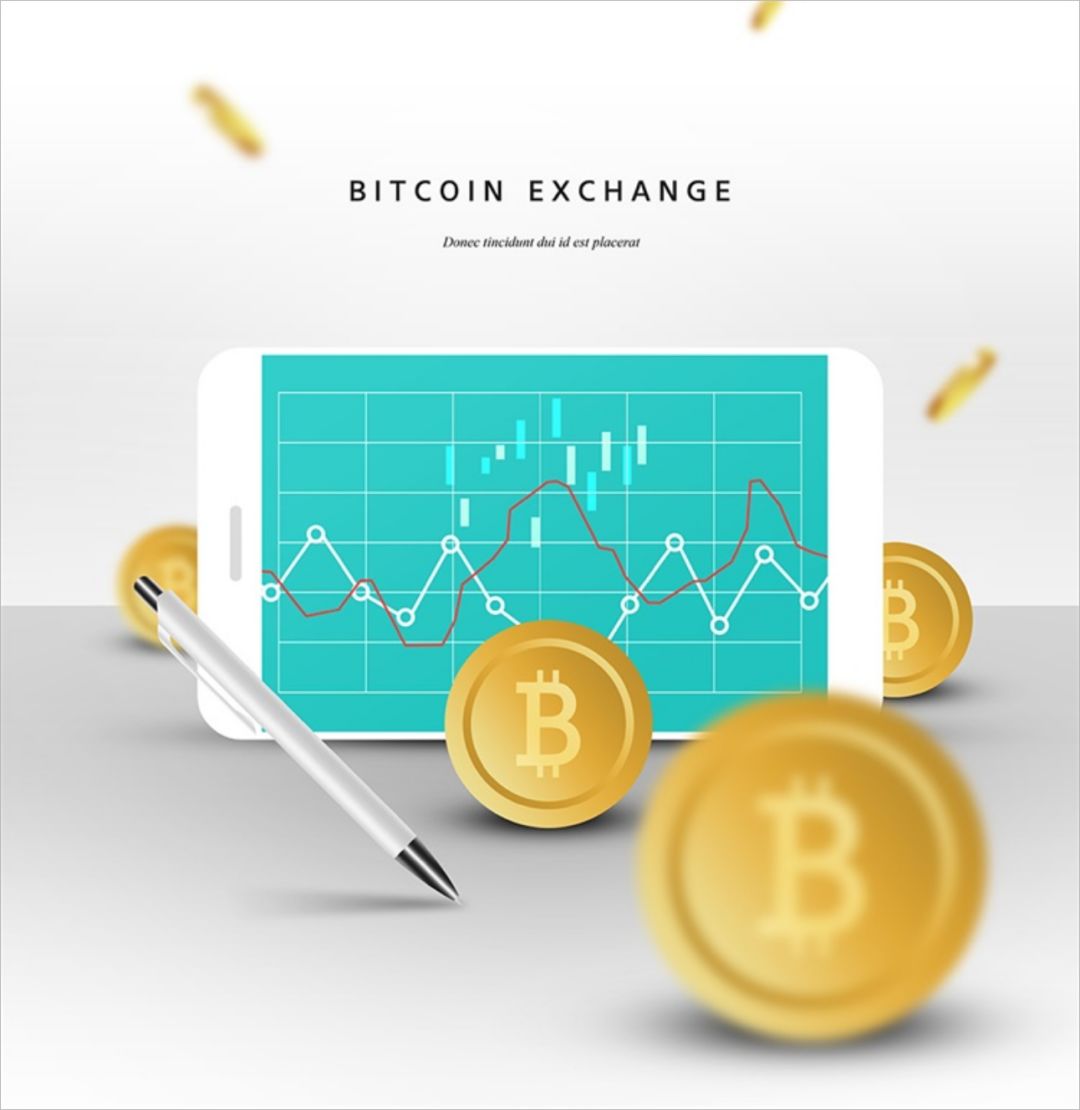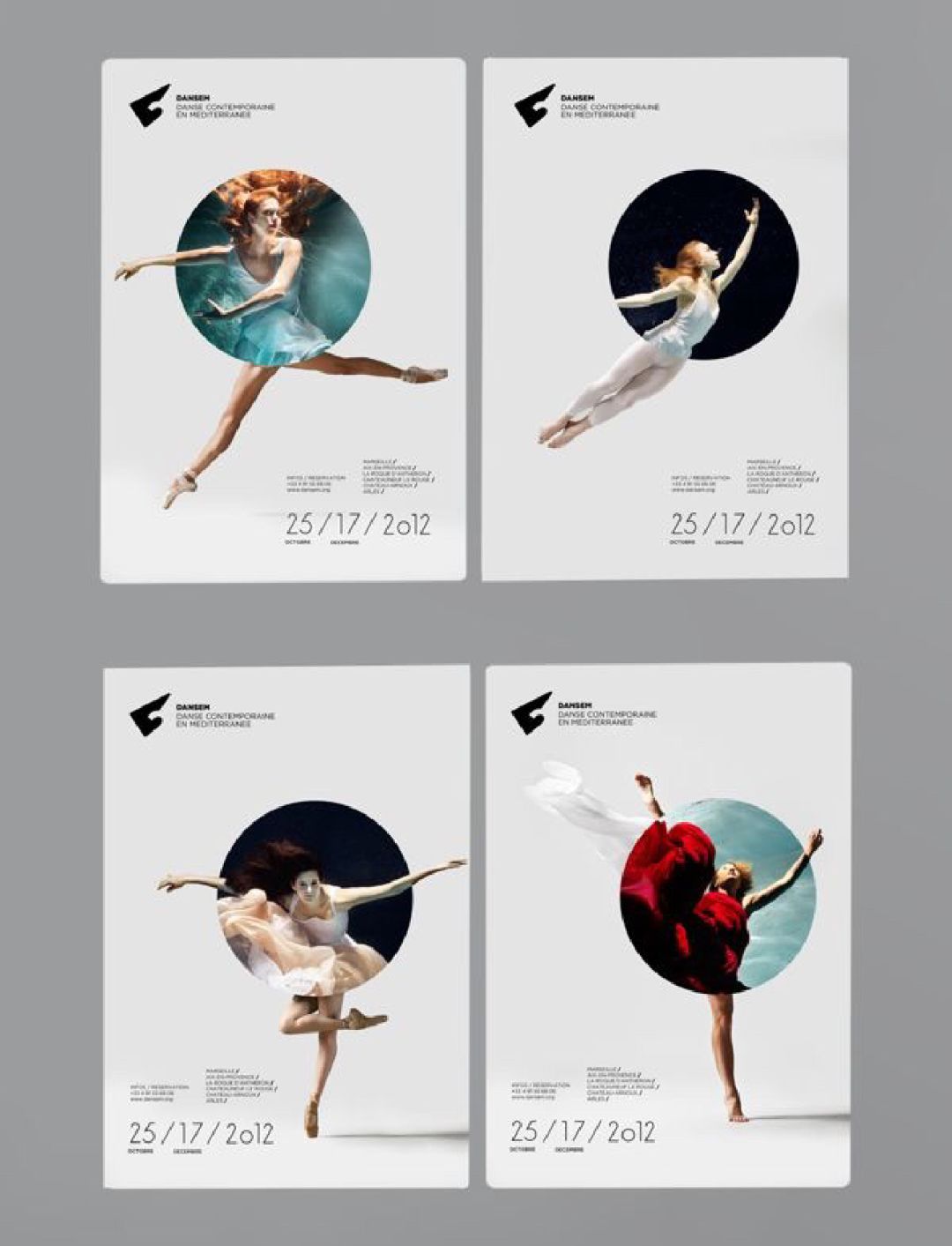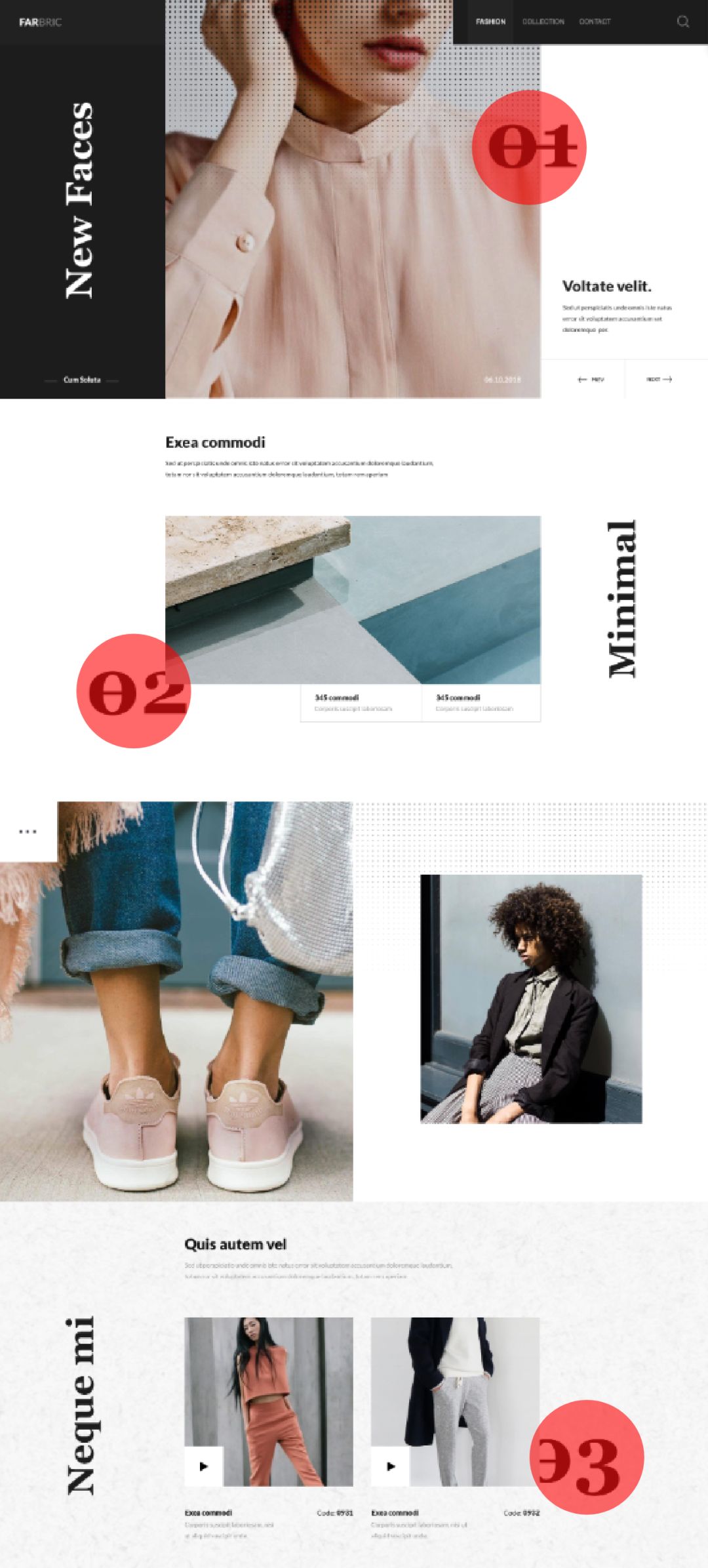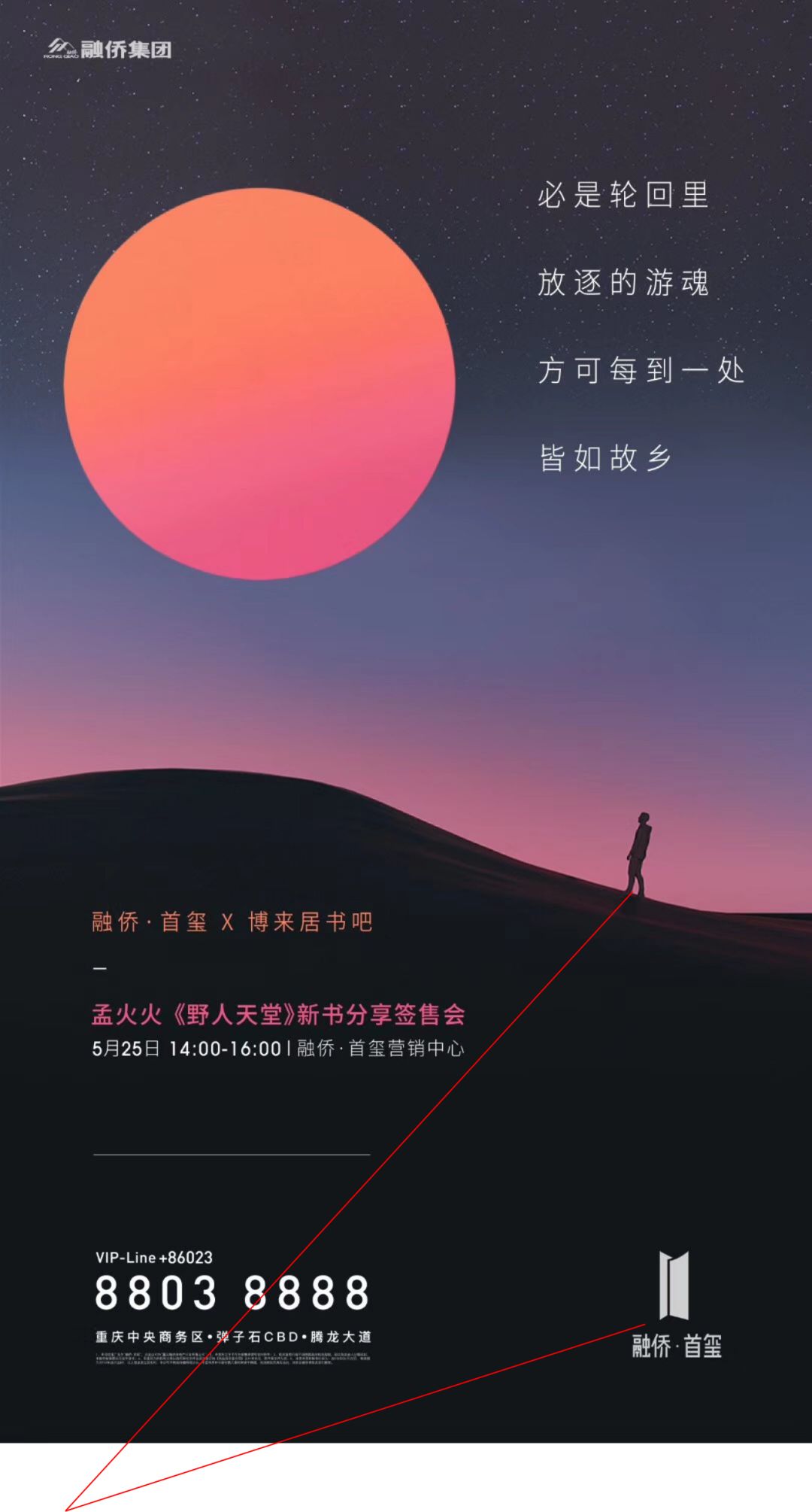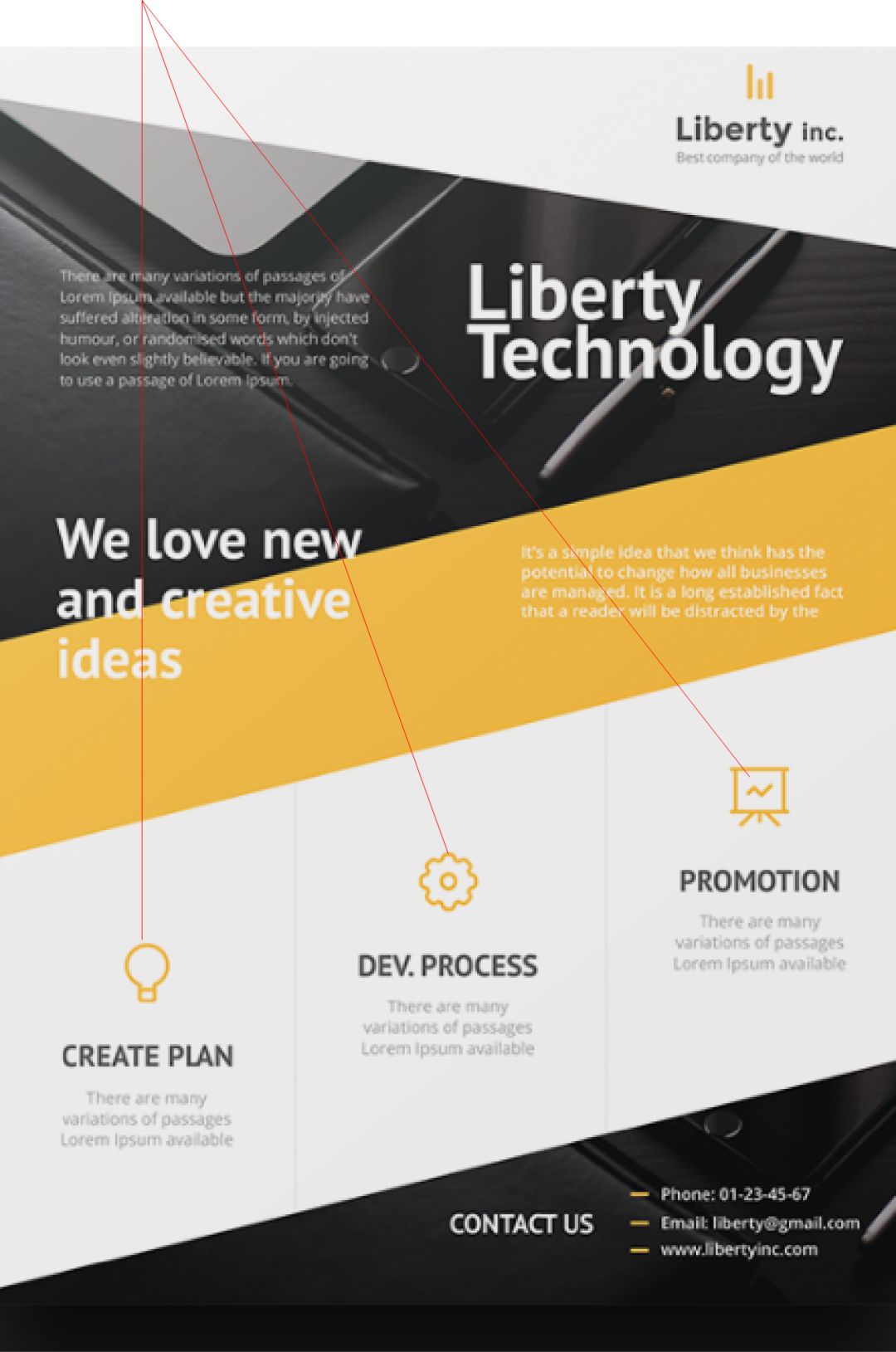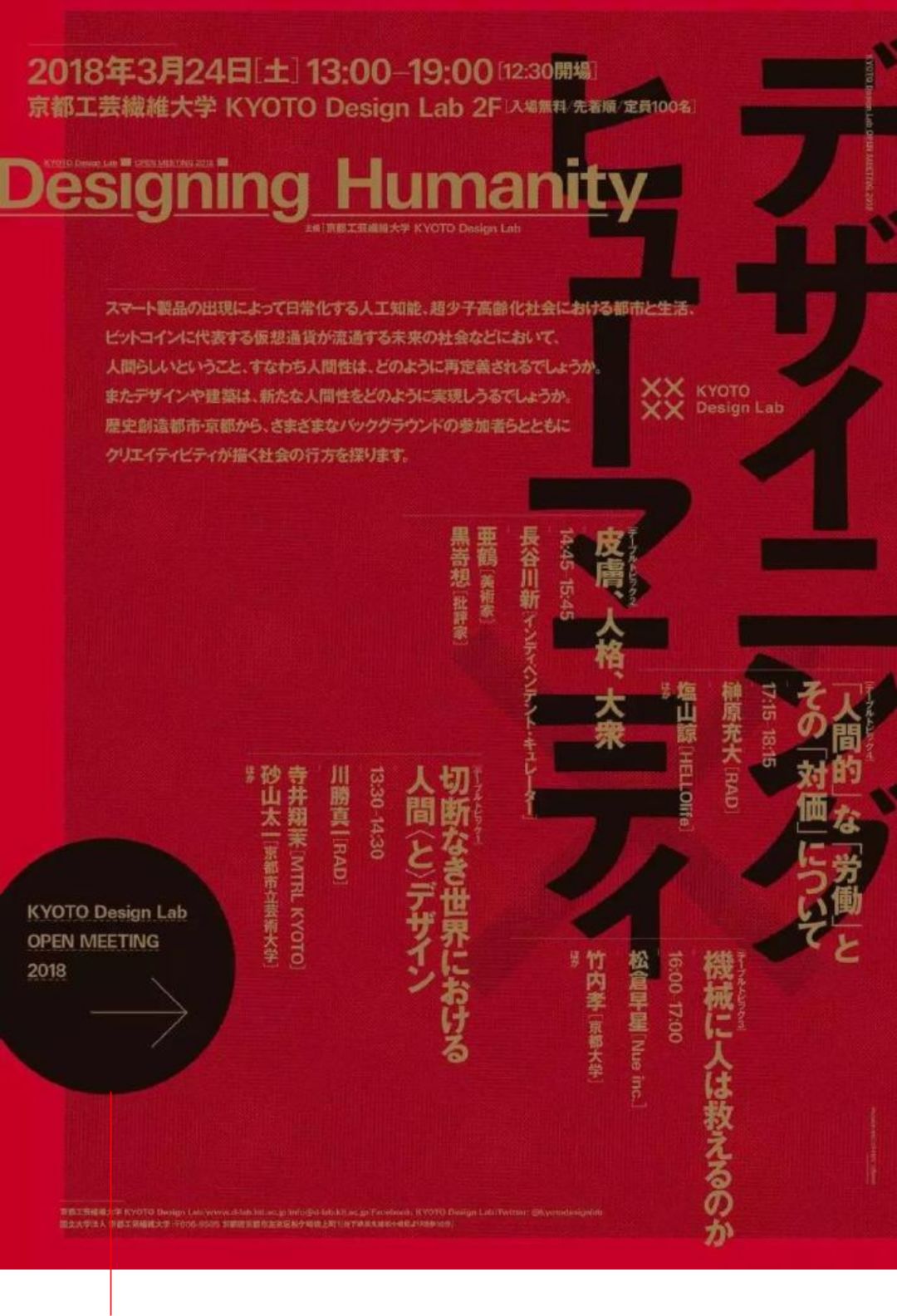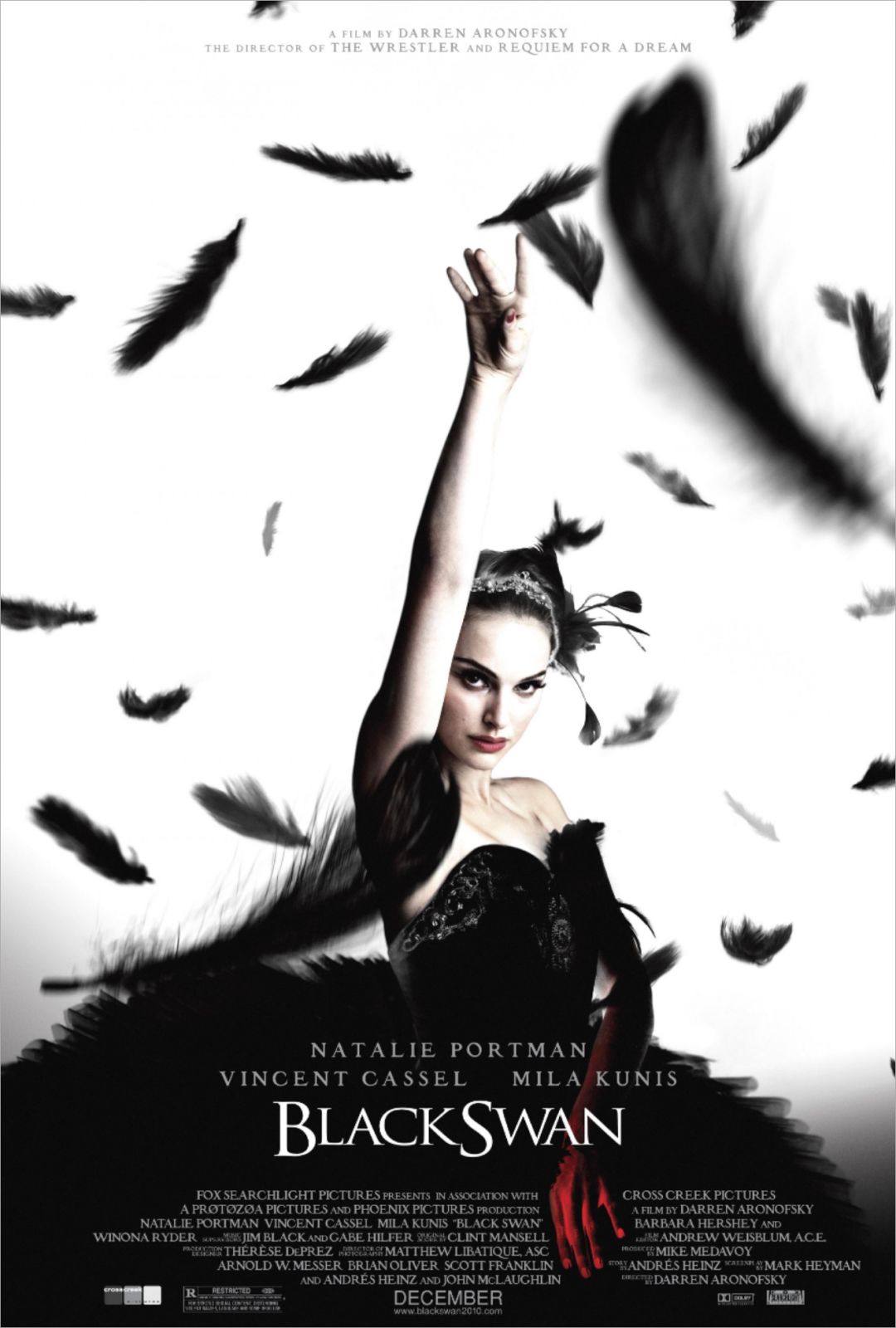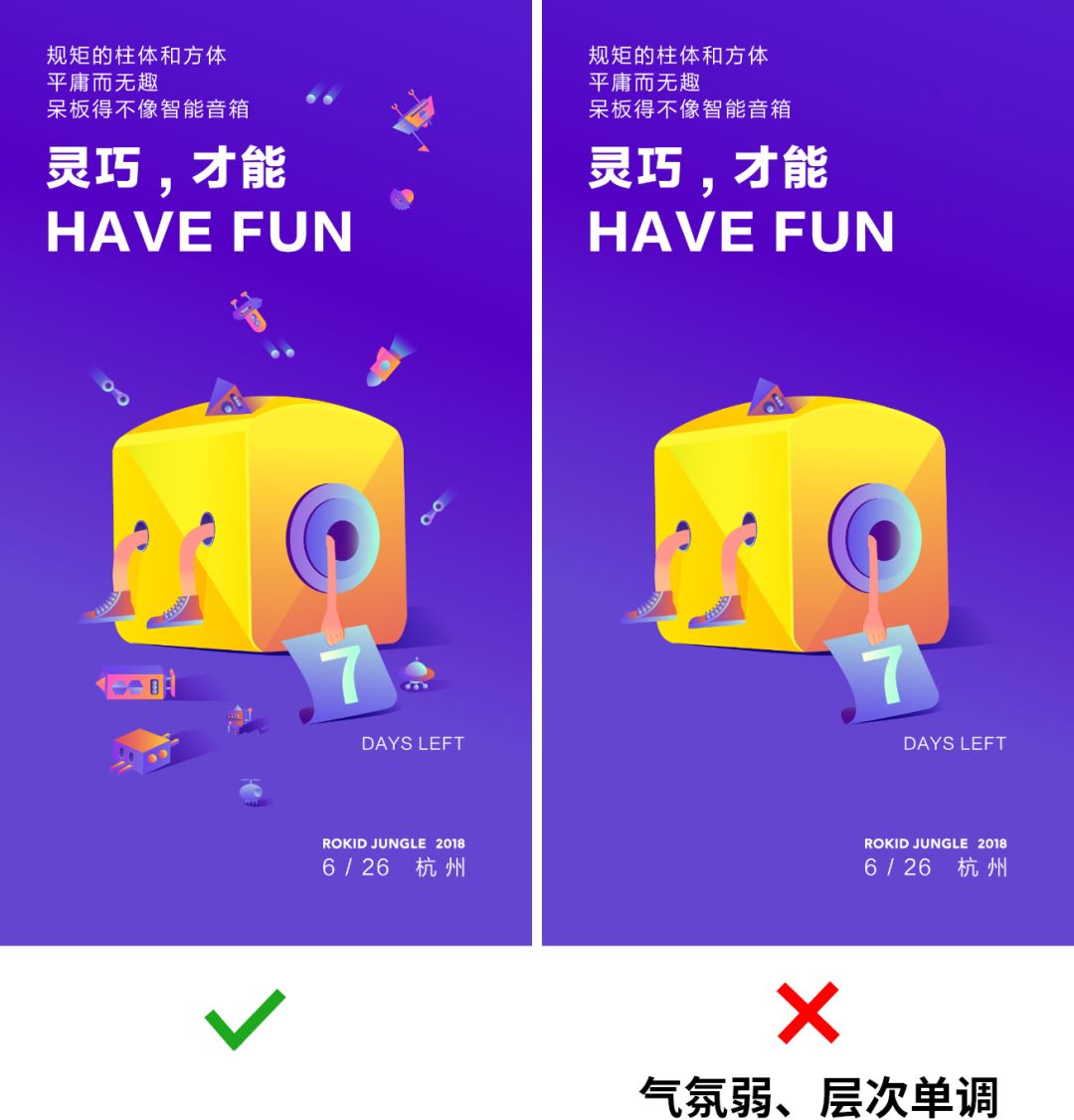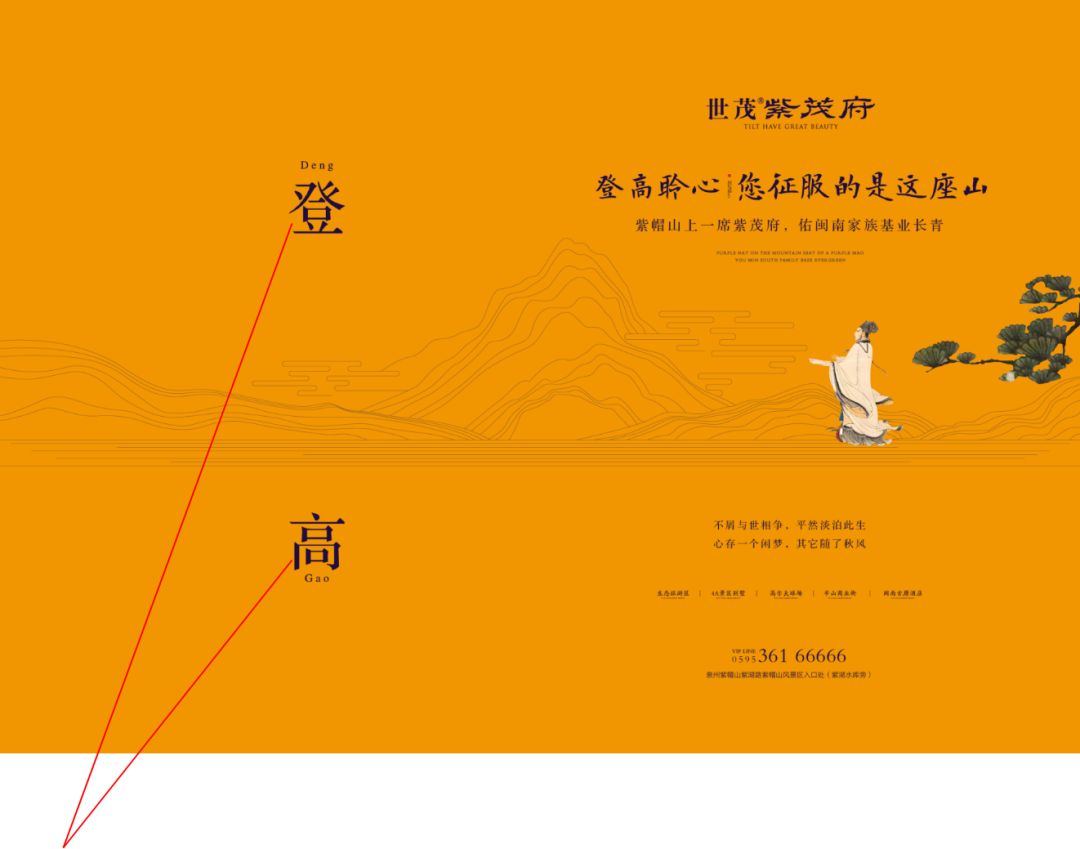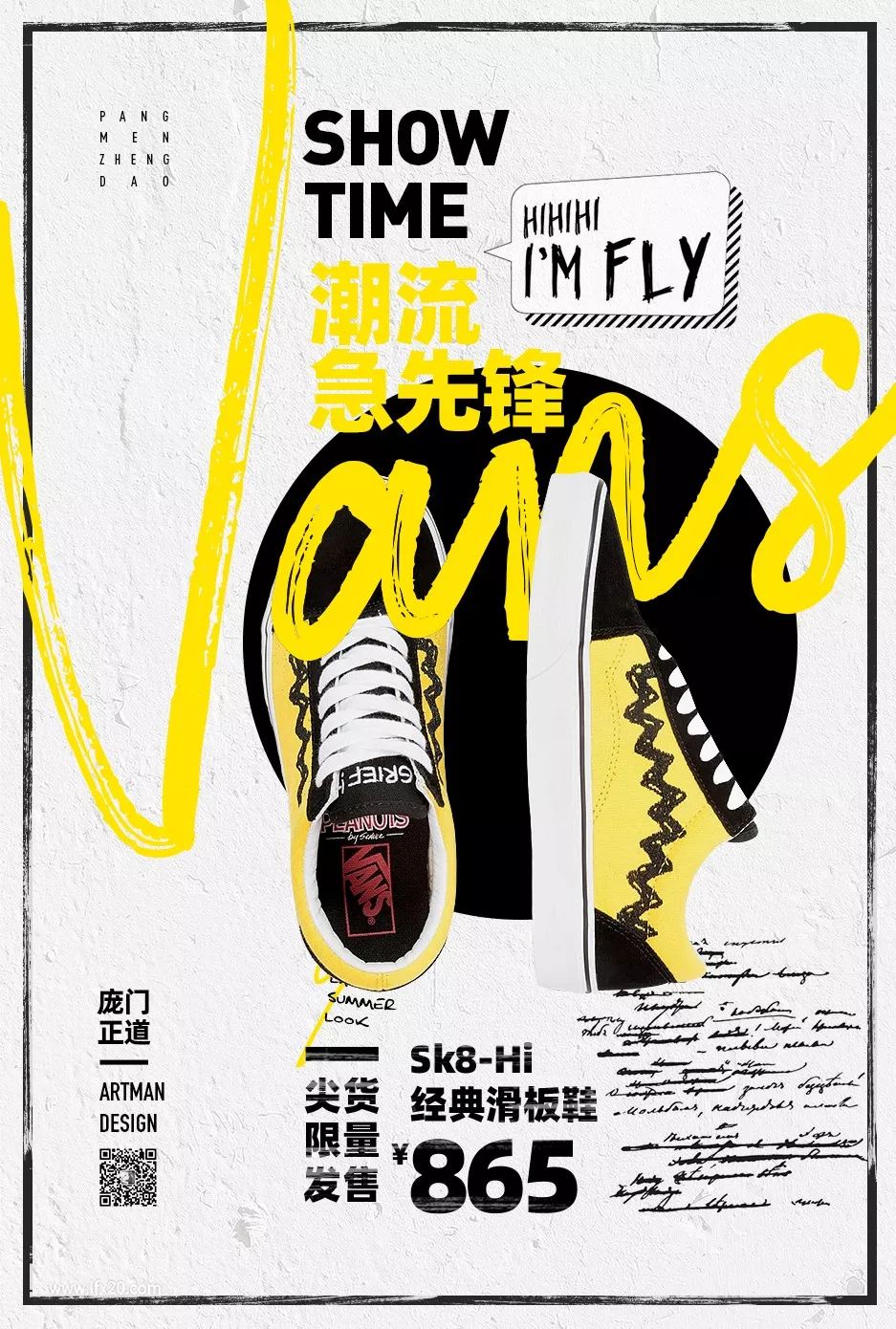
最基础的点线面,才是设计中最重要的语言
在我刚刚学设计时候,我跟绝大多数新手一样,以为只有会火焰效果、金属字、冰块字这些屌炸天的特效才算是牛逼的设计师。于是天天泡在论坛上研究各种特效。
后来,随着自己对设计的认识,才理解真正的设计完全不是这样的。其实最基础的点线面,才是设计中最重要的语言。能够把点线面这种最基础的东西掌握好,才算是对设计入了门。
很多人会觉得点线面嘛,我都学过了,太平淡了,就那点东西。
事实上,点线面的表现力,绝对超出你的想象。
来看看金马奖海报的设计师,用简单的点线面,就勾勒出一幅非常具有艺术表现力的海报。
有时候,简单纯粹,才是最有力量的。
总之,点线面的重要性,怎强调都不为过,接下来我会用三期教程带大家重新认识一下点线面。
今天这期,我们就从“点”开始。
什么是点?
这是个很简单,又很难说清楚的概念。不过我们可以通过它的一些基本特征来定义什么是平面构成中的“点”。
一、点是视觉元素中最小的单元。
这个很容易理解。
平面构成中最基础的元素是点线面,线和面都可以由点延伸出来,所以点自然是最小的单元。
二、点是一个相对概念。
多大的点才是点,这个其实没有绝对的定义。不过在同一个画面中,我们可以通过比较来定义谁是点,谁是面。
三、点不一定是“点”。
这里是说,在具体的画面中,点的表现形式不一定是点状的。看几个例子大家就明白了。
点可以是圈圈。
点也可以是小人。
点还可以是文字。
当然,点还可以是任何形式的。
只要在画面中起到了点的作用,它就是点。
下面我们再来看看点有哪些性格。
上面我们用来定义点的那些特征,都是点的外在表现。
现在我们要讲的点的“性格”,是点的内在。
如果我们把点比作一个人,那它一定是个小孩。
这些关键词是不是跟小孩很像?
所以我们大概可以看出来了,点元素适合用来表达轻松、活泼、喜庆的主题。例如儿童、节日、促销这些气氛比较活跃的设计。
接下来我们再来看看,不同的点,又会表现出哪些不一样的性格。
一、不同位置和方向的点,会给人不同的视觉感受。
在画面最中间位置的点,会呈现出稳定感。
散落的点则会呈现出不稳定、灵动的视觉感受。
在实际的应用中,如果希望页面更加活泼动感,可以给页面增添一些灵活摆放的点元素。
具体案例:
位置在画面偏上的点,会表现出上升的动势,而在画面偏下位置的点,则表现出下坠的动势。
具体案例:
二、不同形态的点,也会给人不同的视觉感受。
面积越大的点,在视觉上会显得离人眼更近。
看具体案例就明白了。
明度越低的点,视觉上会显得重量更重。
如下图所示,在主体上我们可以用明度低的颜色,稳住画面。辅助元素上使用浅色,在视觉上拉开层次。
实点与虚化的点,可以明确画面焦点,让用户视线快速定位到画面的主体上。
通过虚实对比,能迅速的拉开画面前后对比,形成空间感。
好了,了解完点的各种形态和特征之后,下面我们来看看,在实际的应用中,点元素具体都能起到哪些作用。
在大多数情况下,点都被我们当作辅助元素来使用。但实际上,它的应用范围非常广。
一、聚焦主体
当画面中只有一个点存在,那这个点很自然的就成为了焦点所在。
这个点即使是小到快看不见,它依然还是画面的焦点所在。
在实际的应用中,还可以通过留白、颜色对比等方式,强化画面主体。
还可以通过聚拢的方式强化画面中的视觉焦点。
说到聚焦,
二、引导视线
当画面中的信息比较多时,可以适当的加入一些点来引导用户视线。
比如在一个很长的页面中,我们经常会使用数字来引导用户的视线,一方面是提醒用户内容模块的切换,另一方面也让排版的节奏有一些跳跃感。
在杂志的文字排版中,文字和图标都是用来引导视线的常用方法。
同样的手法。
网页设计中的图标,也能起到类似的作用。
三、平衡构图
我们将页面的内容排版做好之后,都需要整体来看一下构图上是不是平衡的,如果有视觉上的落差,则可以考虑加入点元素来使得画面更加平衡、稳定。
来看一下具体的案例。
小人和LOGO的加入,不但使画面有了疏密的节奏变化,对画面构图平衡也起到了非常重要的作用。
黑色色块的加入,使得画面两边的重量达到平衡。
在这个画面中,虽然左边比较空旷,但是“登高”两个字与右边的小人形成了三角构图,使得画面重心非常平稳。
由上面几个案例我们可以看出来,在版式平衡中,点往往可以起到四两拔千斤的作用。
总之,我们可以将点元素视为排版中的万能膏药,哪里需要就可以往哪里加。
四、烘托氛围
将点作为辅助元素,来烘托页面的氛围,这是我们最常见到对点的使用方法。
比如下这张海报,纷乱的黑色羽毛让整个画面极富张力。
想象一下,如果把画面中飞舞的小羽毛去掉,那整个画面的氛围将大大减弱,气韵全无。
适当的点缀元素可以很好的丰富画面的层次感,强化整体氛围。
再看一个案例:
画面太空,又不想增加乱七八糟的小元素进来?
将文字散开,化为装饰元素充满整个画面,在保持画面简洁的同时,也非常具有设计感!
分析了一通理论之后,接下来到了动手实操的时候了。
点在实际的应用中,一般分为单点和多点。它们虽然都是点,但是性格却是各异:
单点最大的视觉特征是聚焦,能帮我们强化画面的主体。
而多点更多散漫,动感,适合营造丰富、活泼的气氛。
下面我就以单点和多点两种形式,分别做一个案例。
案例一
单点聚焦
首先抠一双某潮牌的鞋子,为了让它更突出,我在它的下面加了一个黑块,这样就形成了一个聚焦的点。
选一个涂鸦风格的英文字体打上品牌的名字,然后与鞋子做一点穿插的效果。这样整个版式在视觉上就形成了很强烈的动态变化。
接着添加其它文案信息,因为画面整体是偏街头风格的,所以在字体上选择更现代的粗黑体。
添加背景纹理。
选用斑驳的墙面作为背景,与整体的商品的街头风呼应。
最后再添加一些涂鸦风格的小元素,丰富一下画面细节,就完工了!
看看最大图的效果:
接下来我们再来看看多个点的案例。
案例二
多点扩散
还是鞋子,我们先乱七八糟的抠一堆放到页面上,考虑到最终是散落摆放的,所以在选择图片的时候,尽量选不同角度的。
先大致的把鞋子摆放一下,按照从上往下掉的方式,穿过主标题。
然后给每个鞋子添加一点阴影效果,这样看起来会更有立体感。
在背景上添加一些墙面斑驳纹理,再添加一个风格接近的边框,让画面信息更收拢一些。
最后再将文案排上去,注意文字和商品图的穿插关系。
因为商品图数量比较多,而且位置分布和样式都比较零乱,所以文字排版要尽量工整、对齐。
到这里画面就完工了。
我们来简单分析一下点元素的分布。
大致有如下的规律:
1、主体的商品多排布在画面正中间,这样会让整个画面的重心更聚焦一些。
2、散落在两边的辅助点元素可以用视觉上轻量一些的文字。
3、在数量分布上,底部更多一些,这样在视觉上会更平稳一些。
大图走一波。
关于点的教程就到这里了,
下期将会介绍线,敬请期待。